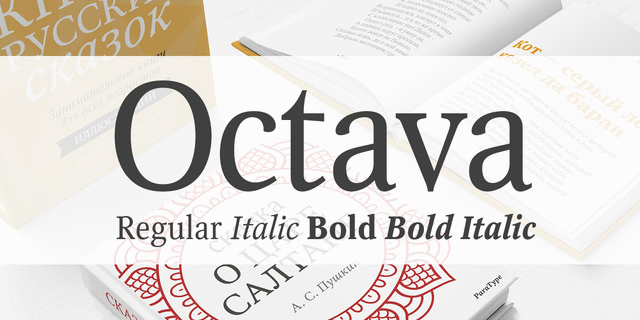
Шрифт Octava (Октава) относится к классу современных вариаций новостильной антиквы. Его разработка была заказана Российским Библейским Обществом, и изначально шрифт был выпущен в трех начертаниях под названием Scriptura Russica в 1996 году. Позже к существующим начертаниям были добавлены знаки латиницы и дополнительно спроектирован жирный курсив. Рисунок шрифта разработан по мотивам шрифтов Lectura (1969, Дик Доойес) и Stone Print (1991, Самнер Стоун). Благодаря компактности формы и крупному очку строчных он обладает повышенной емкостью и хорошей читаемостью в мелких кеглях. Название Октава означает, что шрифт был специально спроектирован для 8-пунктового набора. Все начертания имеют дополнительные комплекты минускульных цифр, а прямое нормальное начертание также капитель. Спроектирован Владимиром Ефимовым и выпущен компанией ParaType в 2001 году. В 2012 году шрифт был незначительно доработан и перевыпущен.
Ассоциации c начертанием Octava BoldКачества и характер:
мотивирующий, ответственный, важный, серьезный, классический, традиционный, гармоничный, благородный